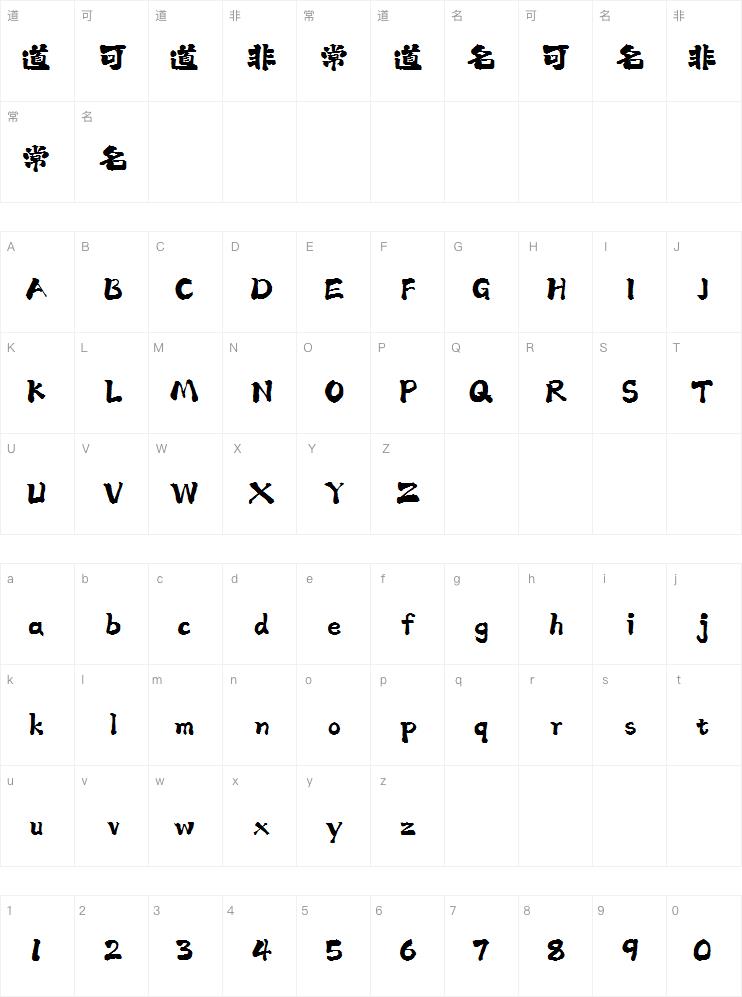
上首天涯书法体,笔法灵动,笔画形态富有变化,起笔、行笔、收笔处模拟传统毛笔书写韵味,或藏锋蓄势,或露锋显锐,提按转折间尽显灵动自然,规避机械刻板之感。结构稳健,在遵循汉字结构规律基础上,适度夸张与变形,重心平稳又不失活泼,部分笔画巧妙穿插、呼应,增强整体视觉张力与和谐感。适用于搭配标志、广告标语、商业广告等高端属性。